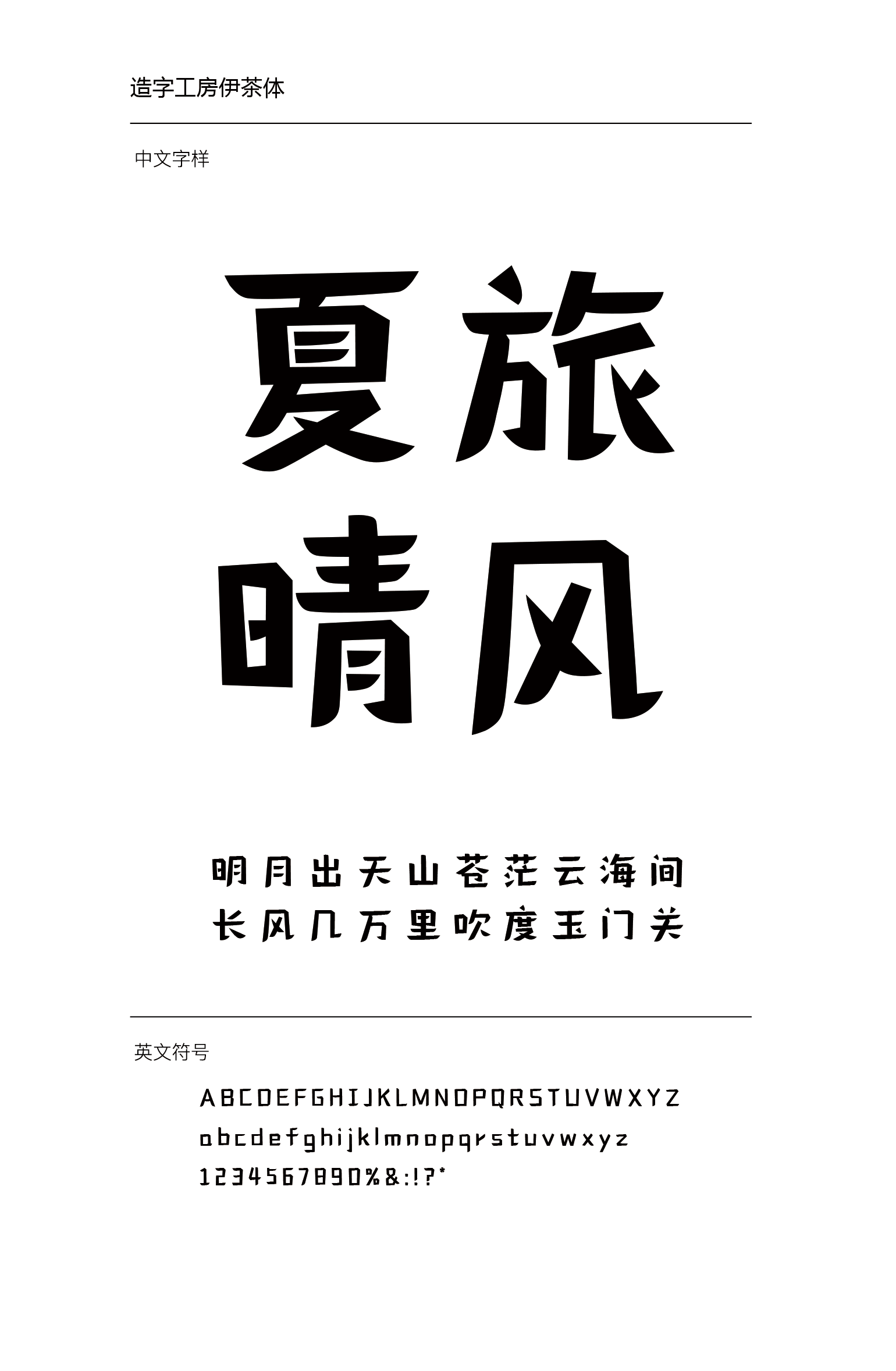
造字工房伊茶体设计说明
造字工房伊茶体,其笔画利落、钩角凌厉,横折处做斜切处理,雕琢精致,似茶叶中粗头尖,使字形丰富灵动,游刃有余,赋予字体一种侘寂美感。高低错落的处理方式,令字体笔画更加随性舒展,极富趣味性。此款字体适用于大标题及个性品牌设计推广等环境。有着极强的应用空间。本字体为简体字库,采用OpenType/CID格式,Adobe-GB1-5编码。基于中华人民共和国GB2312-80字符集标准,另按需添加101个汉字。共收容字数6864CJK汉字,ASCII常用字符100个。